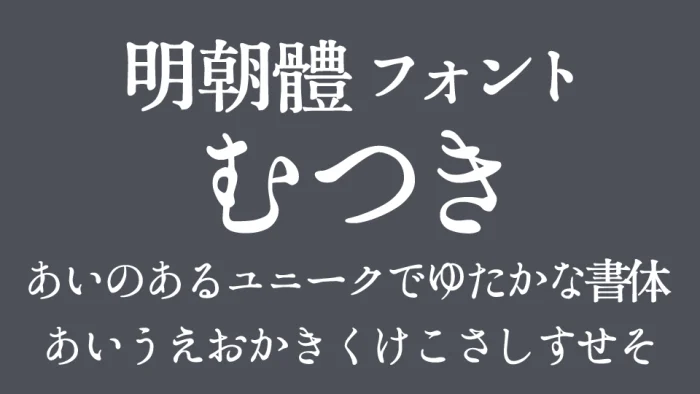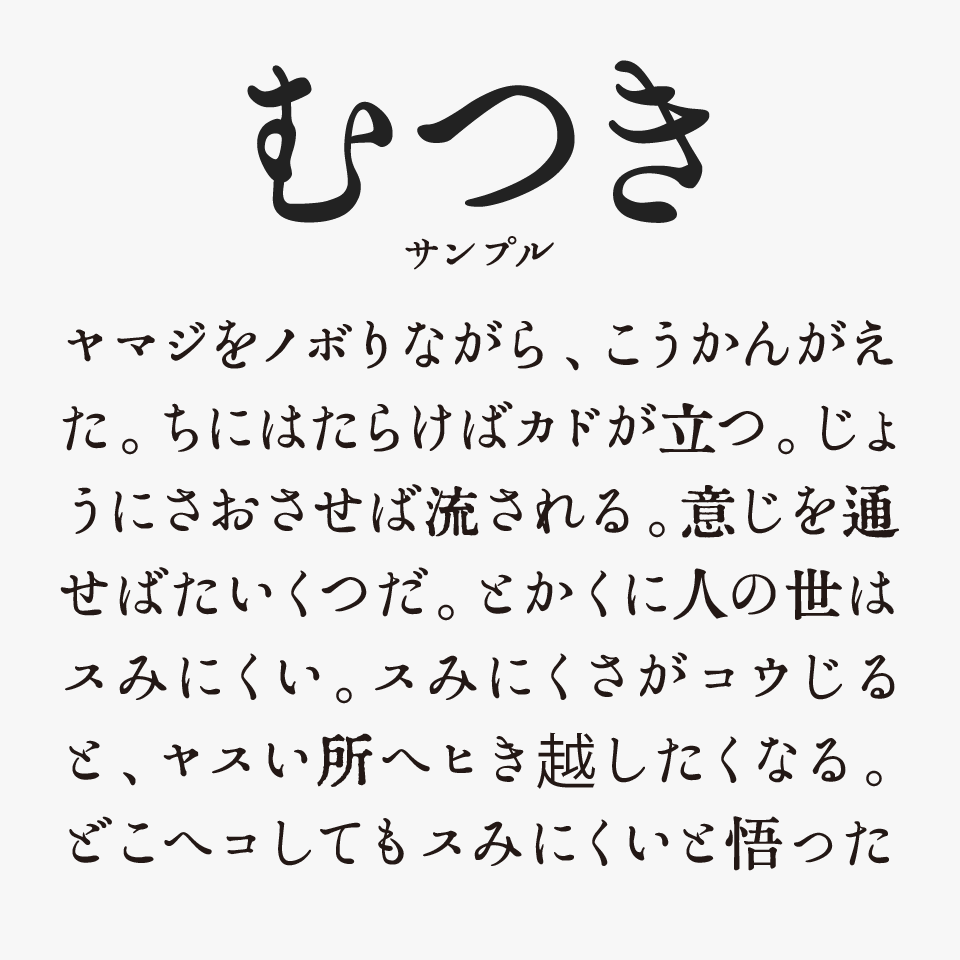
明朝體フォント むつき
明朝體フォント むつきは、「GL-築地五号」をベースに制作された、大正時代の活字文化を思わせるレトロな雰囲気が魅力の明朝体フォントです。
古い書籍や文芸誌に使われていそうな落ち着いた空気感がありながらも、どこか人の手で流れるように書かれたようなやわらかさが感じられるところが特徴です。
横画や払いにはほんのり揺らぎがあり、活版印刷のような懐かしさと、筆文字のような自然な流れが心地よく混ざり合っています。
収録文字は、ひらがな・カタカナ・漢字は少数のみの収録となっているため、他のフォントと混植で使うことをオススメします。